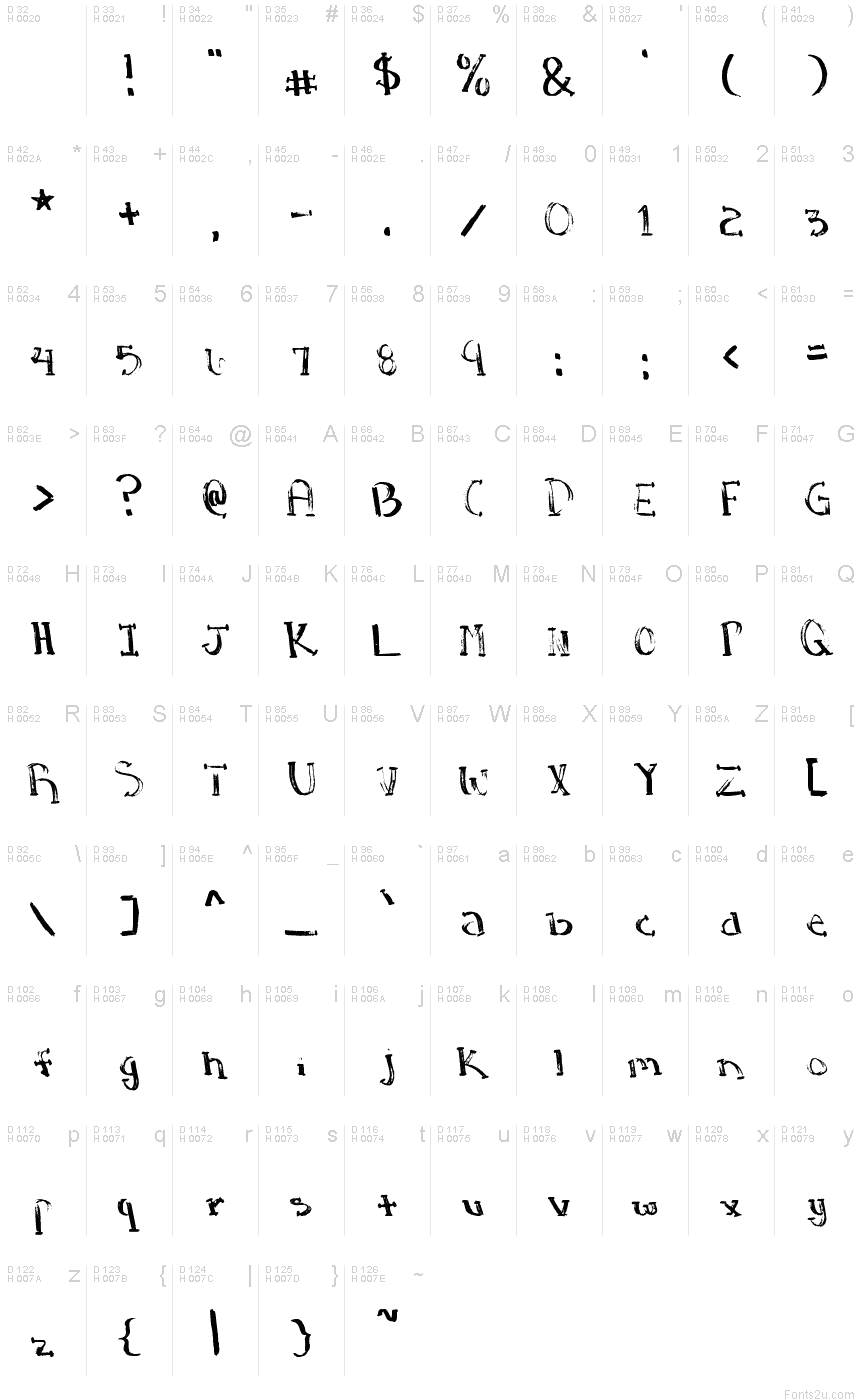
Stopwatch od Jasona Skooga je bezplatné, erodované display písmo s nádechem starého tisku. Písmena vypadají ošoupaně, skvrnitě a mírně nepravidelně, jako by pocházela z opotřebovaného razítka nebo hrubého tiskařského lisu, a mají neotřelé detaily připomínající patky, díky nimž font nepůsobí jen jako obyčejný grunge.
Hodí se pro projekty, které chtějí působit lidsky a lehce ošlehaně: titulky plakátů, obálky zinů, indie obaly, letáky na akce a popisky jsou pro toto bezplatné písmo jako stvořené. Vzhledem k tomu, že hlavní roli hraje textura, nejlépe vynikne v krátkých blocích textu, kde mohou naplno promluvit zlomené hrany a neobvyklé tvary.